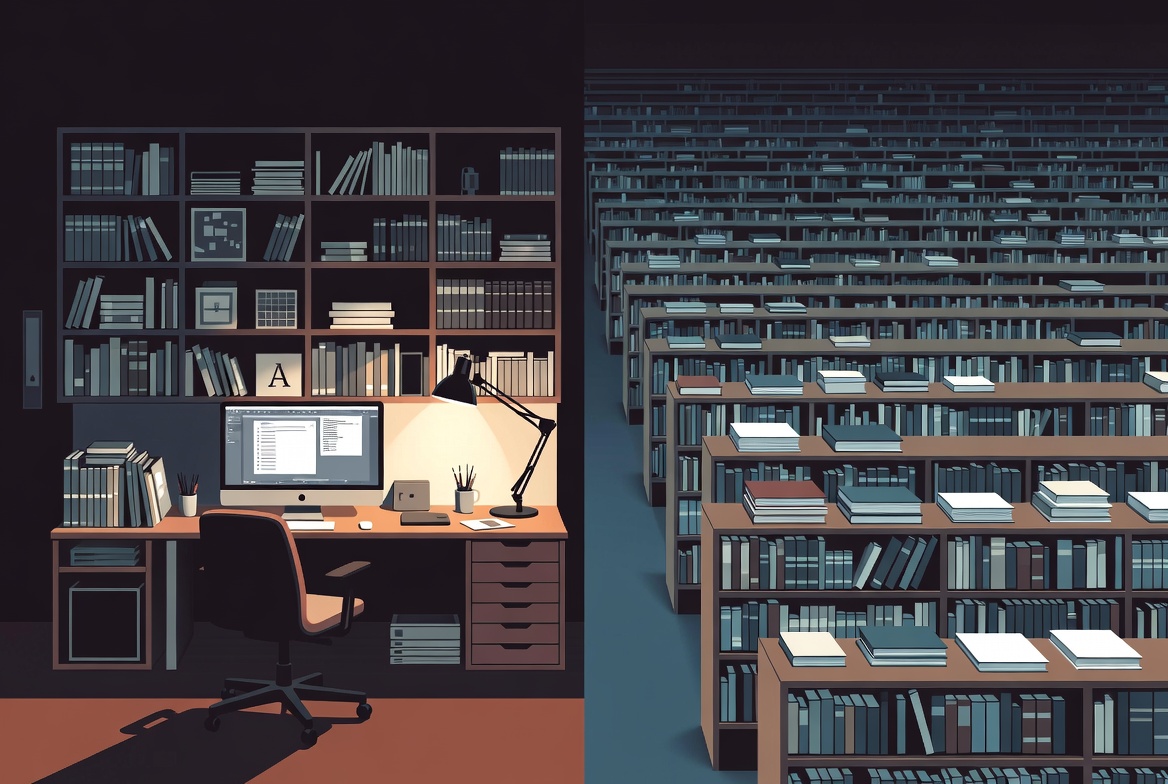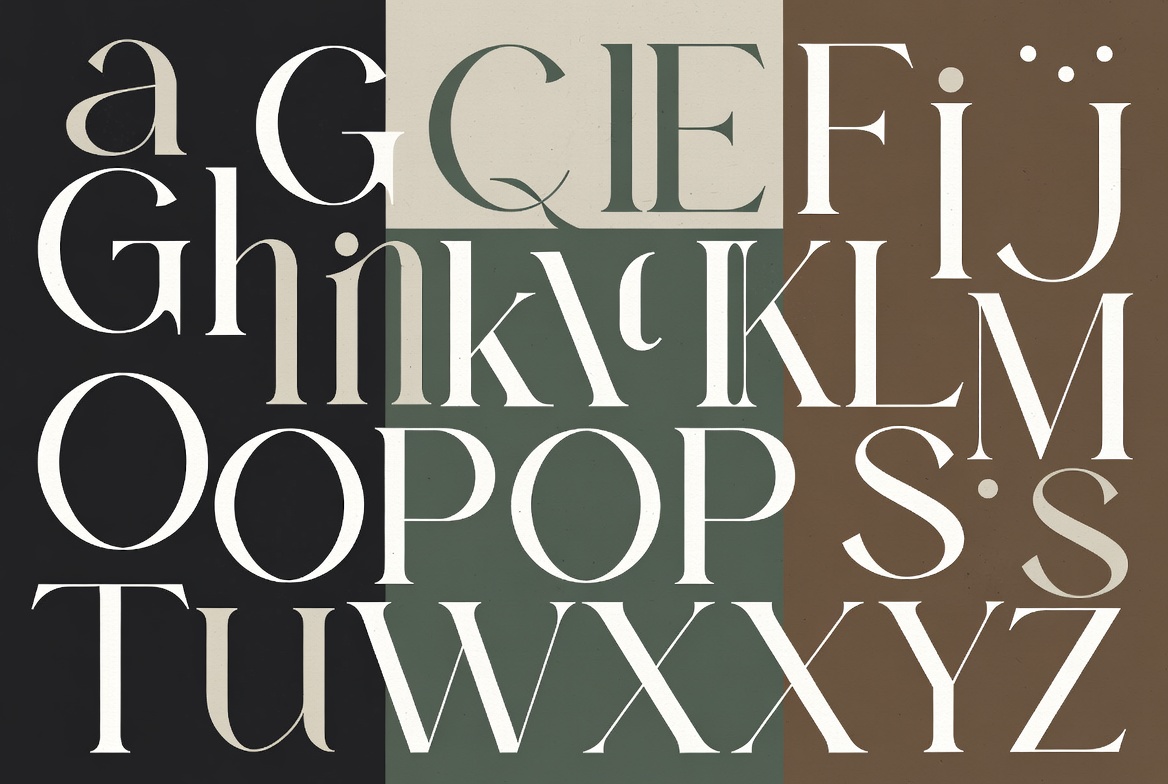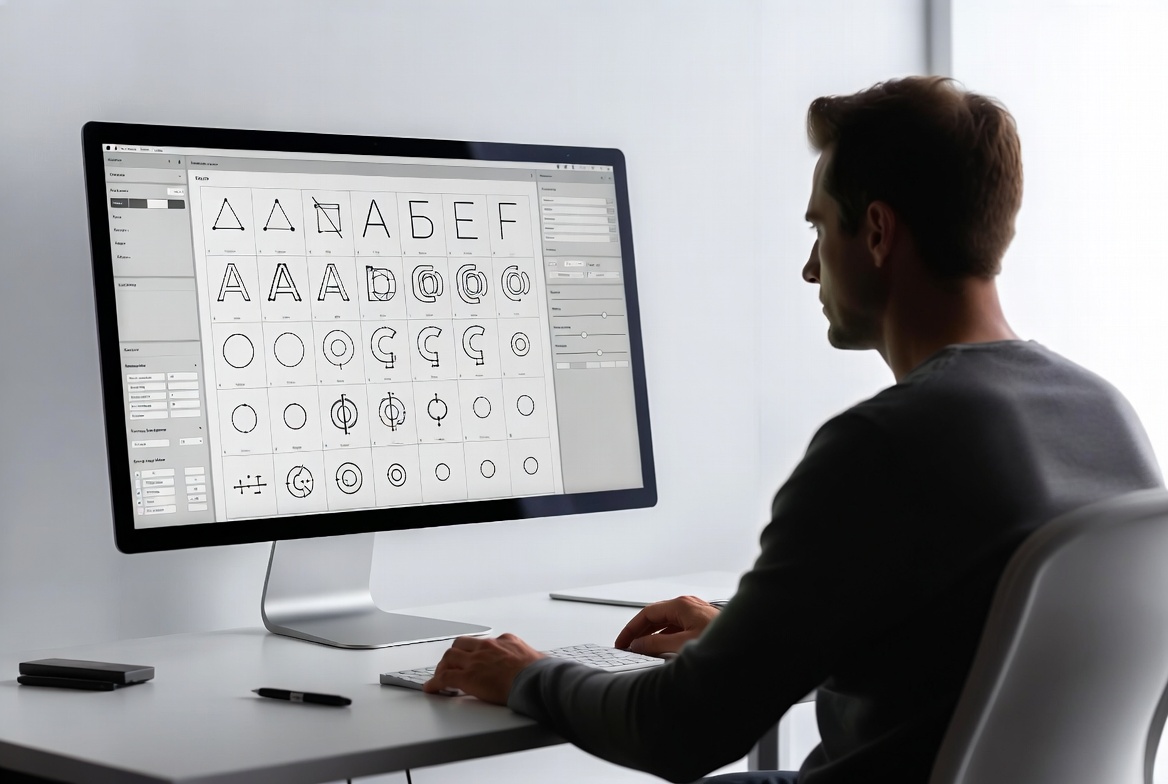
Schriftenhersteller – Teil 3: Bedeutende unabhängige Foundries
Was unabhängige Type Foundries auszeichnet und welche Studios heute besonders einflussreich sind – von Commercial Type über Klim bis Underware.
Nachdem wir uns im letzten Teil die großen Player der Branche angesehen haben, richtet sich der Blick nun auf die unabhängigen Foundries. Gerade sie haben in den letzten zwei Jahrzehnten maßgeblich zur gestalterischen Vielfalt und Qualität digitaler Schriften beigetragen.
Was unabhängige Foundries auszeichnet
Unabhängige Type Foundries arbeiten in der Regel kleiner und fokussierter als die großen Konzerne. Viele bestehen aus nur wenigen Personen oder sogar aus einem einzelnen Designer. Das hat Konsequenzen:
- Die Schriften entstehen oft aus einer klaren gestalterischen Haltung heraus.
- Der Kontakt zu den Designern ist direkter.
- Viele Foundries spezialisieren sich auf bestimmte Schriftgattungen, Sprachen oder Einsatzbereiche.
- Die Qualität der Zeichnung, des Spacing und der technischen Ausarbeitung steht häufig im Vordergrund.
Gleichzeitig müssen unabhängige Foundries wirtschaftlich bestehen und ihre Schriften selbst vermarkten. Das führt zu sehr unterschiedlichen Geschäftsmodellen – von klassischen Lizenzverkäufen bis hin zu Subskriptionsangeboten.
Typedesigner bei der detaillierten Arbeit an Schriftzeichen
Ausgewählte unabhängige Foundries
Die folgende Auswahl ist bewusst nicht vollständig. Sie zeigt vielmehr einige Studios, die in den letzten Jahren besonders einflussreich waren und bei Designern und Agenturen hohes Ansehen genießen.
Commercial Type
Gegründet von Paul Barnes und Christian Schwartz. Commercial Type steht für sorgfältig gezeichnete, oft historisch informierte Schriften mit starker Präsenz in Editorial Design und Corporate Identity. Viele ihrer Familien sind auf lange Lesestrecken und hohe typografische Ansprüche ausgelegt.
Klim Type Foundry
Das neuseeländische Studio von Kris Sowersby gehört zu den profiliertesten unabhängigen Foundries der Gegenwart. Klim-Schriften zeichnen sich durch präzise Zeichnung, gute Lesbarkeit und eine zurückhaltende, aber charakterstarke Formensprache aus. Viele Designer schätzen die Konsistenz und den handwerklichen Anspruch.
Underware
Das niederländische Trio ist bekannt für experimentierfreudige und zugleich gut nutzbare Schriften. Underware verbindet spielerische Ideen mit solider handwerklicher Ausführung und hat über Jahre hinweg immer wieder ungewöhnliche, aber praxistaugliche Konzepte vorgelegt.
Hochwertige Letterformen als Ausdruck unabhängiger Schriftgestaltung
TypeTogether
TypeTogether hat sich besonders im Bereich mehrsprachiger und redaktioneller Schriften einen Namen gemacht. Das Studio legt großen Wert auf gute Lesbarkeit, umfassende Zeichensätze und die Unterstützung vieler Sprachen – ein klarer Vorteil für internationale Projekte.
Weitere erwähnenswerte Studios
Neben den genannten Foundries gibt es eine Reihe weiterer unabhängiger Studios, die regelmäßig Aufmerksamkeit erhalten, darunter Production Type, Dinamo, Bold Monday, Sharp Type oder OH no Type Co. Viele von ihnen arbeiten an der Schnittstelle zwischen experimenteller Formfindung und professioneller Nutzbarkeit.
Warum unabhängige Foundries relevant bleiben
Trotz der Marktmacht großer Anbieter spielen unabhängige Foundries weiterhin eine wichtige Rolle:
- Sie erweitern die gestalterische Bandbreite über die Standardbibliotheken hinaus.
- Viele innovative Entwicklungen (z. B. bei Variable Fonts oder speziellen Schriftschnitten) entstehen zuerst in kleineren Studios.
- Für Projekte mit hohem gestalterischem Anspruch bieten sie oft die interessanteren Alternativen zu den „Hausschriften“ der großen Plattformen.
Gleichzeitig stellt die wirtschaftliche Situation vieler unabhängiger Foundries eine Herausforderung dar. Die Konsolidierung des Marktes und die starke Präsenz großer Bibliotheken machen es kleineren Anbietern nicht leicht, Sichtbarkeit und nachhaltige Einnahmen zu erzielen.
Symbolische Darstellung: Fokussiertes unabhängiges Studio gegenüber einer großen anonymen Schriftbibliothek
Ausblick
Im nächsten Teil dieser Serie beschäftigen wir uns mit größeren unabhängigen Foundries, die kommerziell stärker und produktiver aufgestellt sind als die klassischen Boutique-Studios – darunter auch TypeType. Danach folgen spezialisierte und besonders innovative Anbieter.